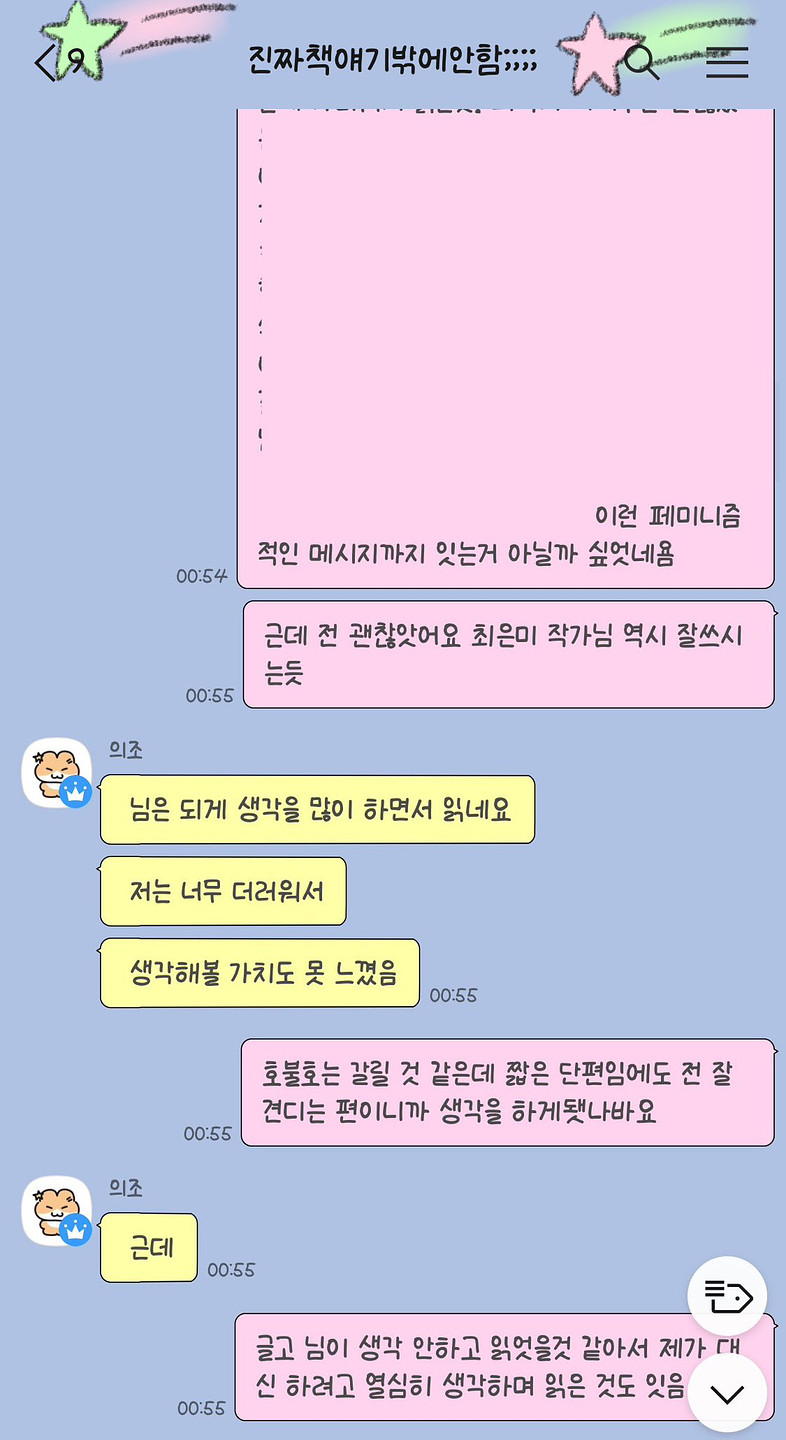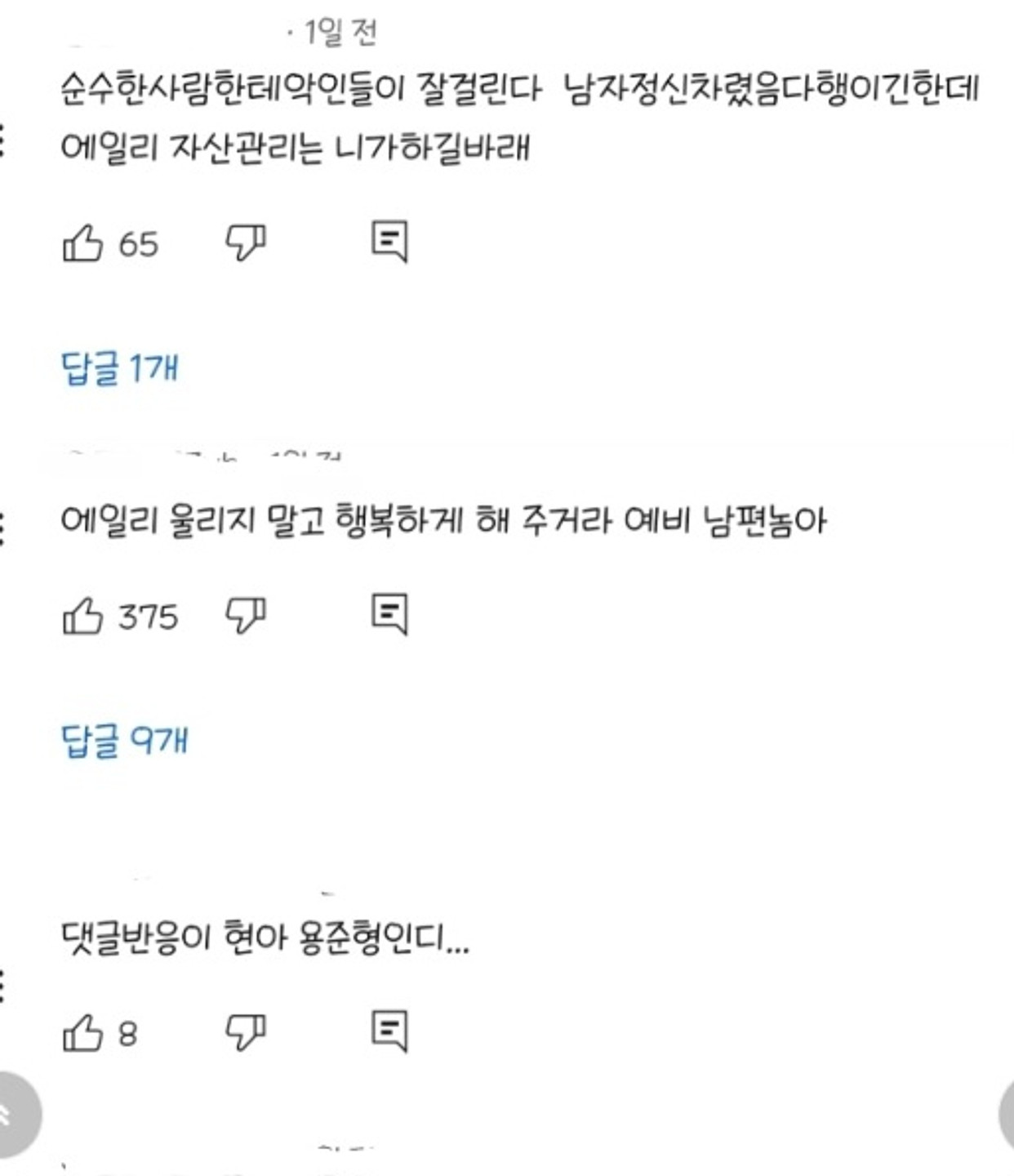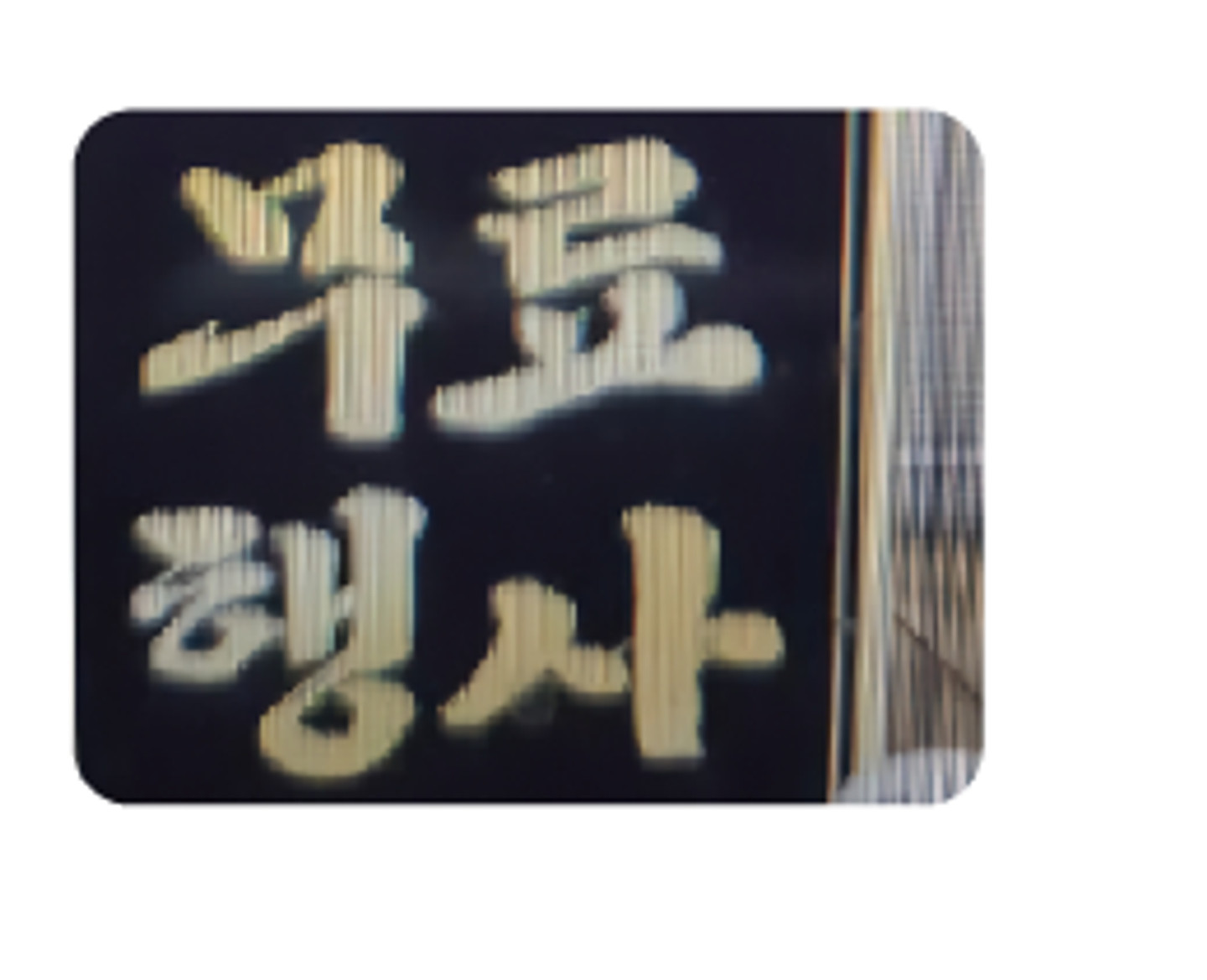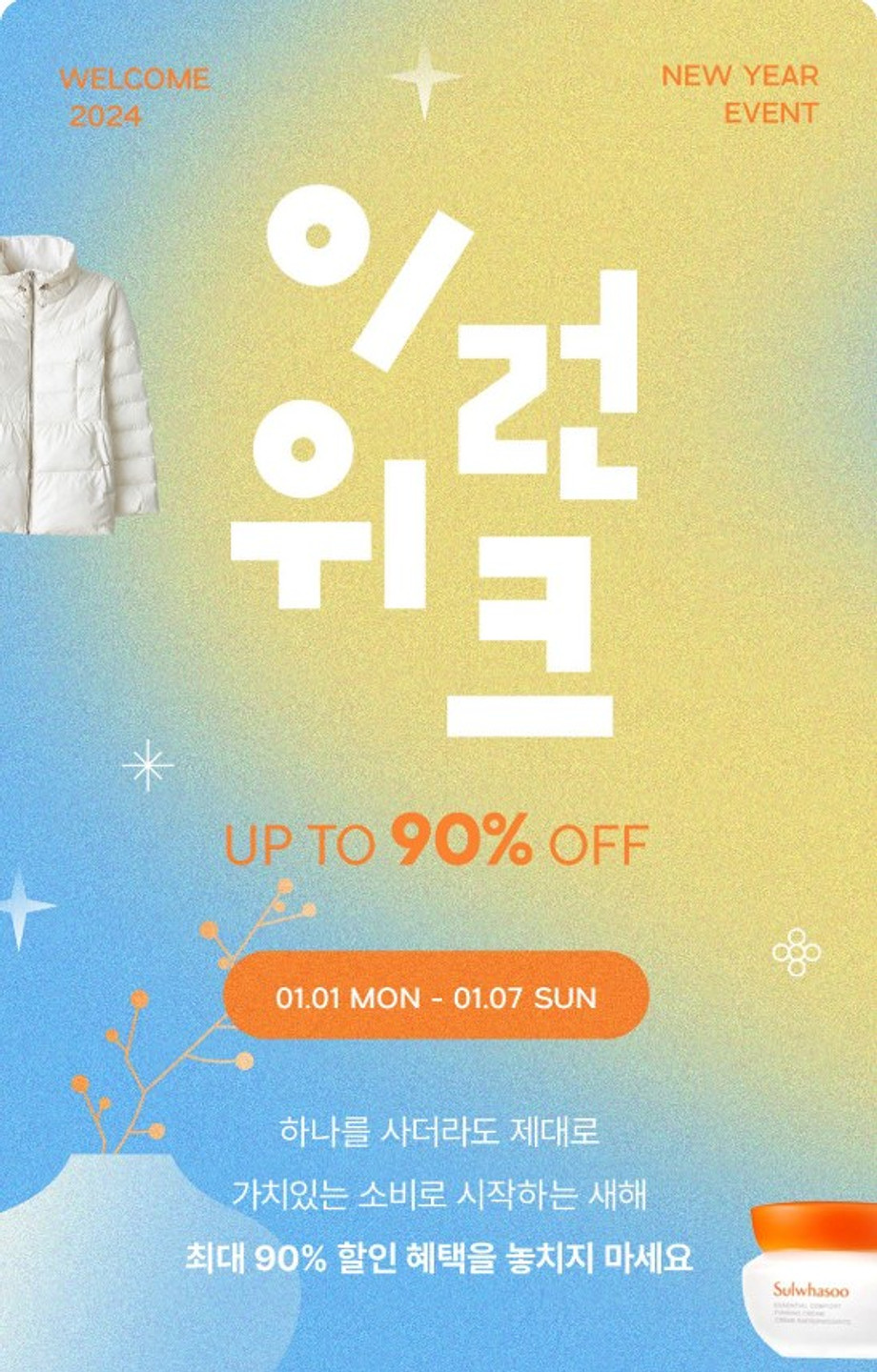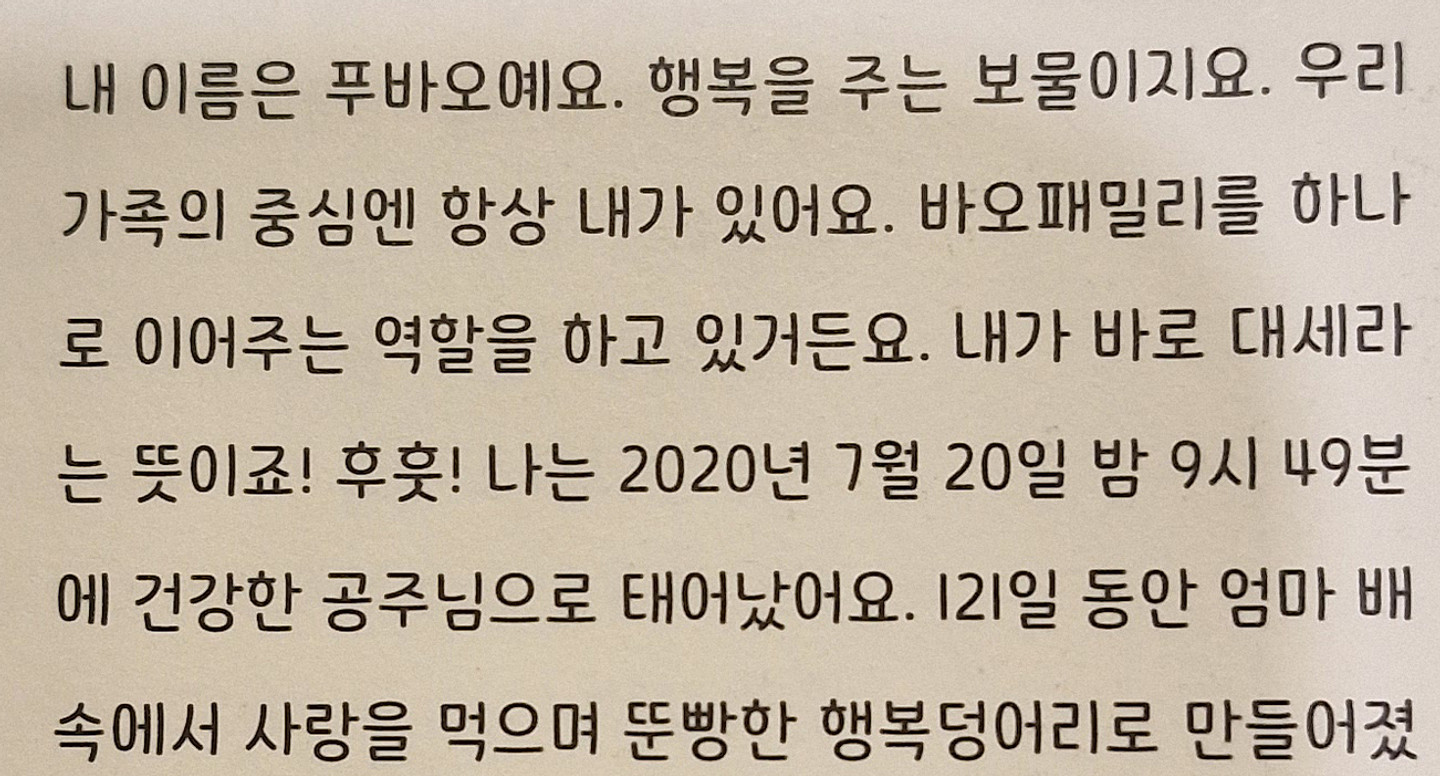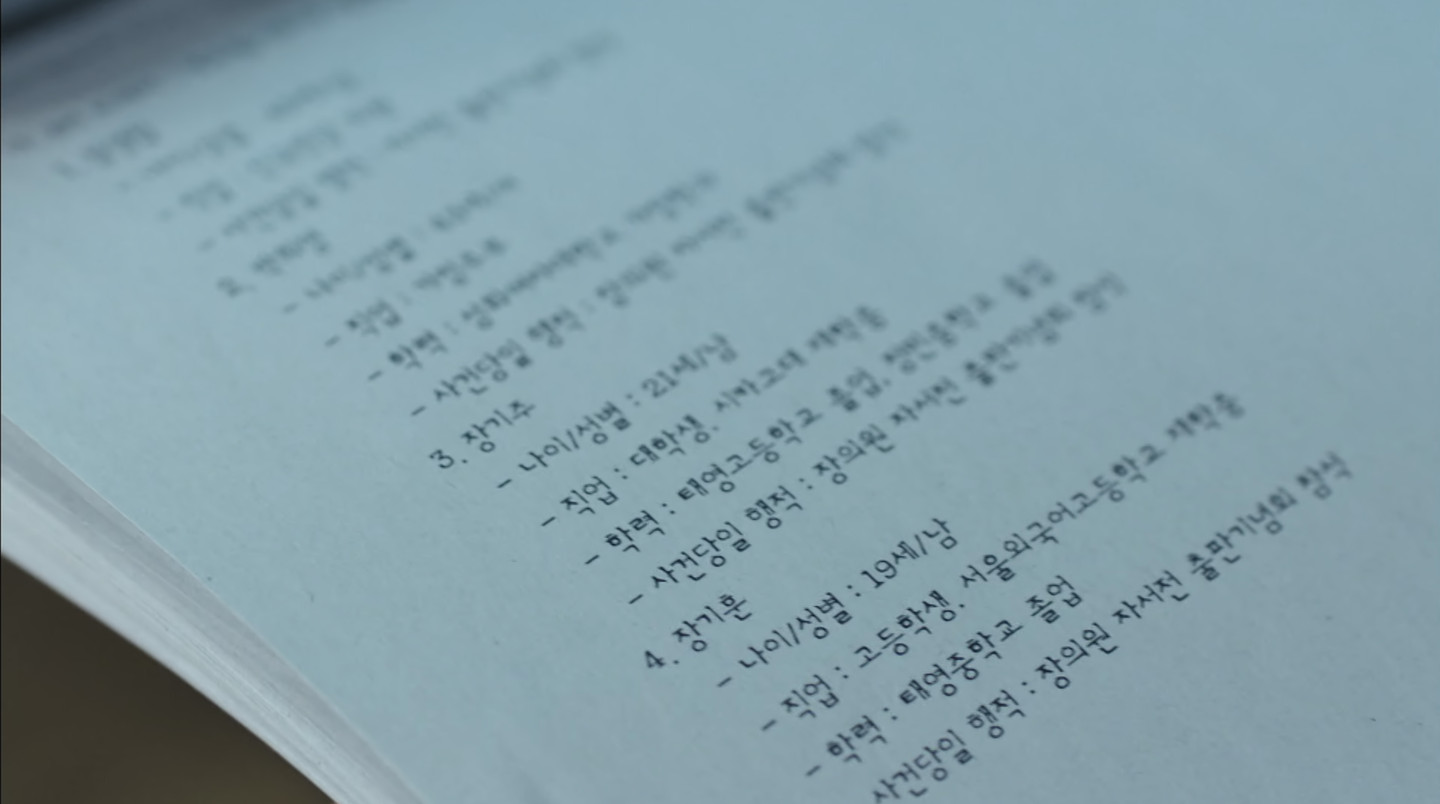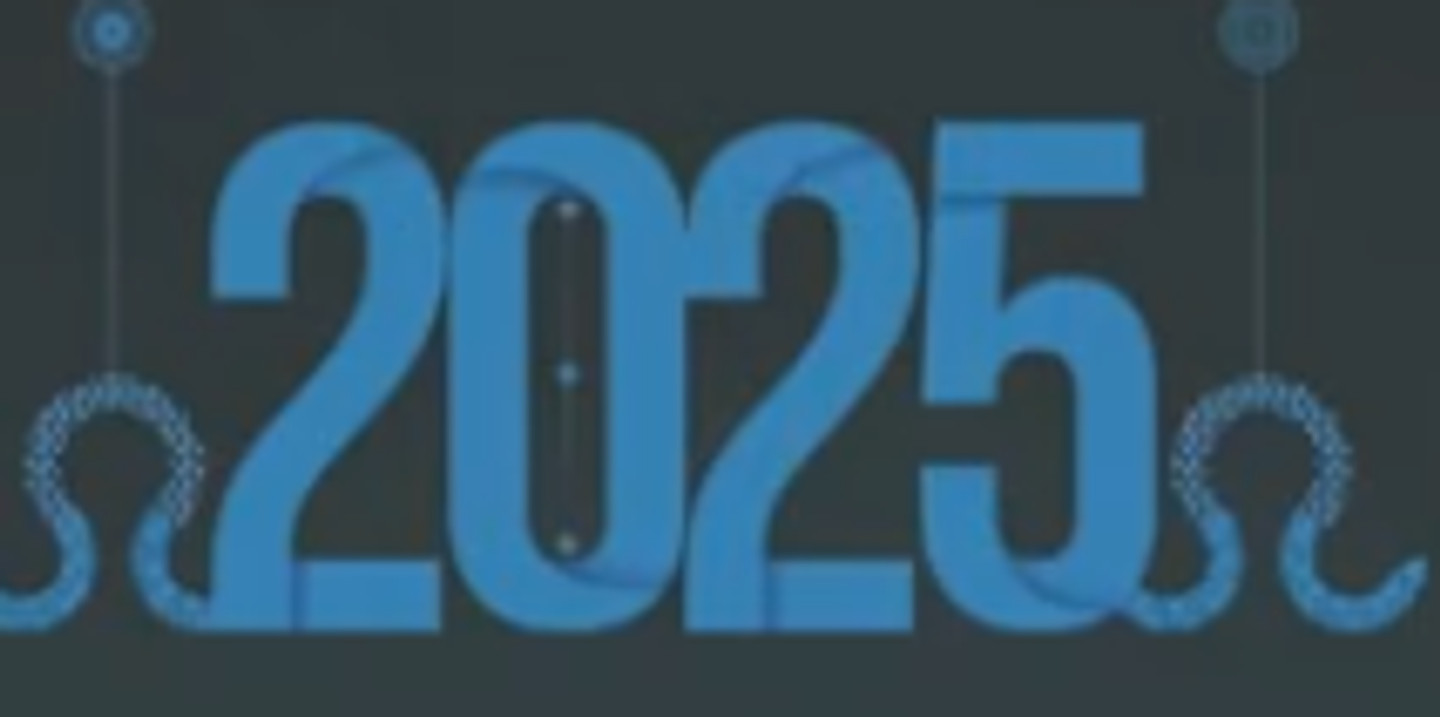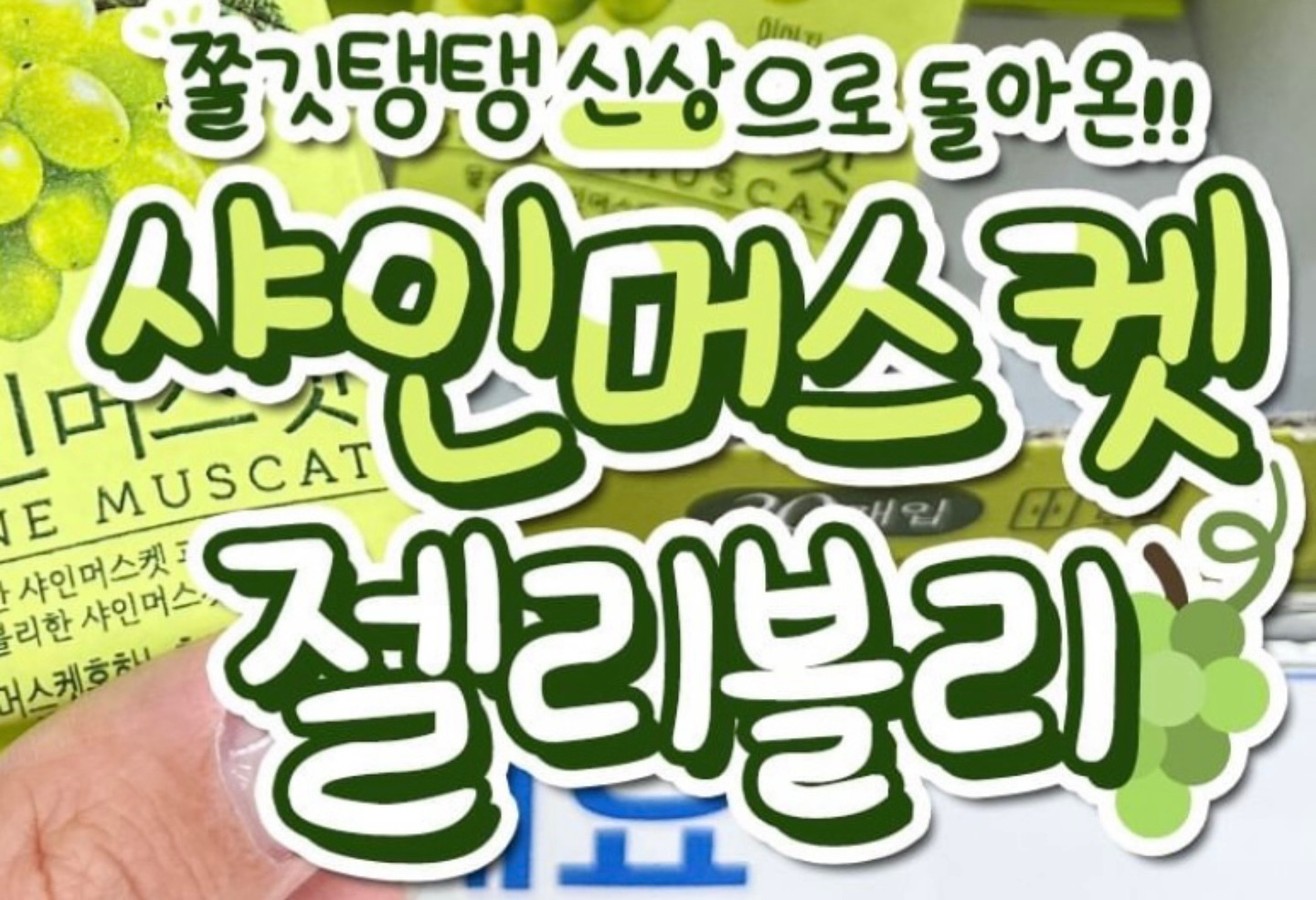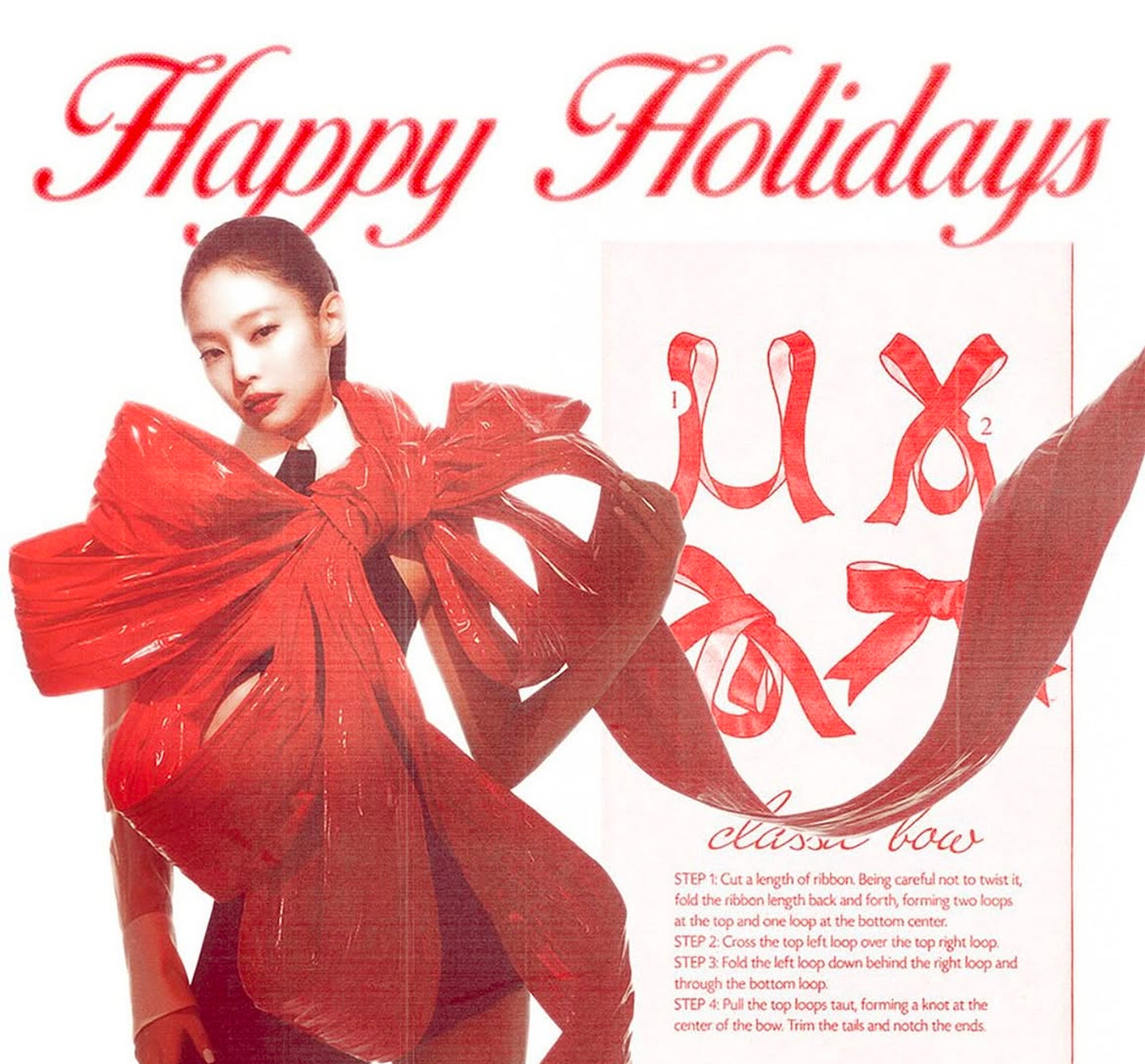
한글폰트 무슨 폰트인가요?
알려주세용
고운 빛 그림전 무슨 폰트일까요..?
느림공간 폰트랑 아래 작은 글씨 폰트를 알고싶어요
안녕하세요..!! 자막으로 쓰인 폰트가 어디서 많이본건데 ㅠ 못찾겠네요.. 어떤글씨체인지 아시는분 계실까요..
해당 폰트 너무 알고 싶어요ㅜ 콘트라스트 폰트 아닙니다! ㅠ
어린이 도서관 무슨서체 일까요?
글씨체 문의드립니다ㅠㅠ
폰트서체좀 알려주세요
이 폰트 아시는 분 있을까요?
손글씨 폰트인데 어떤 폰트인지 알고 싶습니다
요즘 영상에 많이 보이는 고딕인데요.. 애플고딕 같은데 맞나요?? 휴먼고딕이랑 좀 헷갈리네요 ㅠㅠ 둘 다 아니면 어떤 폰트인가요?
이거 폰트 어떤거인지 알수 있을까요?
폰트 뭘까요!!!
폰트 궁금합니당
이 폰트 이름 아시는 분 있나요..? 유튜버 써니 님입니다
무슨 폰트일까요(?)
공부왕에서 쓰는 폰트인데 어떤건지 알고싶어요
또박또박한데 진짜 손글씨같아서 너무 찾고싶습니다ㅠㅠㅠ 무슨 폰트일까용??
https://www.youtube.com/watch?v=1m0gb8OrJ5E 오토하님 영상에 나온건데 너무 궁금해요!!
안녕하세요 이런 엘리베이터나 전자시계에 나오는 숫자 사용할 수 있는 폰트가 있을까요?
무슨 폰트 일까요??
무슨 폰트일까요!? ㅜㅜ
이런느낌의 폰트를 찾고있습니다...혹시 없을까요
포카리 광고인데, 무슨 폰트인가요?
이 영문폰트 뭔지 아시는분 계신가요??
이 츄츄가 무슨 폰트일까요? ㅠ
혹시 무슨 폰트인지 아시나요? 아리따돋움이랑 비슷하지만 장평이 더 작아 홀쭉한 모양입니다. 아무리 찾아도 모르겠네요.
이거 진짜 도대체 무슨 폰트 인가요
위 아래 다 알려주세요 ㅠㅠ
펜타포트 폰트인데 아시는 분 있으실까요?
자막 무슨 폰트인지 궁금합니다!
어떤폰트인가요
예전에 찾아봤었는데 어떤 폰트였는지 까먹었네요ㅠㅠ 어떤건지 알 수 있을까요?
이 폰트좀 알려주세요 제발 부탁입니다!
영문 폰트 무슨 폰트인지 아시는 분 계실까요ㅜㅜ
같은 폰트인데 혹시 폰트알려세요~
"사전예약상품" 글씨가 어떤 폰트 일까요? HY나 휴먼 각 헤드라인하고는 조금 달라서요...
무슨 font인가요?
유튜버 여단오님 30만 큐앤에이 영상입니다 자주 쓰시던데 무슨 폰트인지 궁금해요
유투버 여단오 30만명 큐앤에이 영상입니다 폰트 궁금해요 ㅜㅜ
혹시 이 뭉실거리는 구름같은 영문 폰트 뭘까요…? 한글폰트는 아닌것같은데 일수도 있긴해요… i에 빳칭 빛모양이 특징이에요
이 폰트 좀 알려주세요 부탁입니다
무슨 폰트일까여 ㅜㅜㅠㅠ
어떤 폰트인가요??
한글 폰트랑, 영어 폰트 알 수 있을까요?
무슨 폰트인가요ㅠㅜ
이거 무슨 폰트 인가요ㅜㅜ
두레고속관광 한글폰트랑 영어폰트 궁금해요
썸네일에 들어간 "쌀사자 보이즈 쌀다팜"의 폰트가 궁금합니다